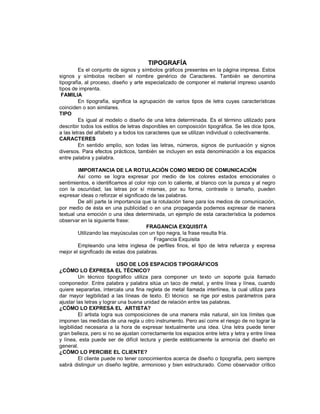
TIPOGRAFÍA
Es el conjunto de signos y símbolos gráficos presentes en la página impresa. Estos
signos y símbolos reciben el nombre genérico de Caracteres. También se denomina
tipografía, al proceso, diseño y arte especializado de componer el material impreso usando
tipos de imprenta.
FAMILIA
En tipografía, significa la agrupación de varios tipos de letra cuyas características
coinciden o son similares.
TIPO
Es igual al modelo o diseño de una letra determinada. Es el término utilizado para
describir todos los estilos de letras disponibles en composición tipográfica. Se les dice tipos,
a las letras del alfabeto y a todos los caracteres que se utilizan individual o colectivamente.
CARACTERES
En sentido amplio, son todas las letras, números, signos de puntuación y signos
diversos. Para efectos prácticos, también se incluyen en esta denominación a los espacios
entre palabra y palabra.
IMPORTANCIA DE LA ROTULACIÓN COMO MEDIO DE COMUNICACIÓN
Así como se logra expresar por medio de los colores estados emocionales o
sentimientos, e identificamos al color rojo con lo caliente, al blanco con la pureza y al negro
con la oscuridad; las letras por sí mismas, por su forma, contraste o tamaño, pueden
expresar ideas o reforzar el significado de las palabras.
De allí parte la importancia que la rotulación tiene para los medios de comunicación,
por medio de ésta en una publicidad o en una propaganda podemos expresar de manera
textual una emoción o una idea determinada, un ejemplo de esta característica la podemos
observar en la siguiente frase:
FRAGANCIA EXQUISITA
Utilizando las mayúsculas con un tipo negra, la frase resulta fría.
Fragancia Exquisita
Empleando una letra inglesa de perfiles finos, el tipo de letra refuerza y expresa
mejor el significado de estas dos palabras.
USO DE LOS ESPACIOS TIPOGRÁFICOS
¿CÓMO LO ÉXPRESA EL TÉCNICO?
Un técnico tipográfico utiliza para componer un texto un soporte guía llamado
componedor. Entre palabra y palabra sitúa un taco de metal, y entre línea y línea, cuando
quiere separarlas, intercala una fina regleta de metal llamada interlínea, la cual utiliza para
dar mayor legibilidad a las líneas de texto. El técnico se rige por estos parámetros para
ajustar las letras y lograr una buena unidad de relación entre las palabras.
¿CÓMO LO EXPRESA EL ARTISTA?
El artista logra sus composiciones de una manera más natural, sin los límites que
imponen las medidas de una regla u otro instrumento. Pero así corre el riesgo de no lograr la
legibilidad necesaria a la hora de expresar textualmente una idea. Una letra puede tener
gran belleza, pero si no se ajustan correctamente los espacios entre letra y entre línea
y línea, esta puede ser de difícil lectura y pierde estéticamente la armonía del diseño en
general.
¿CÓMO LO PERCIBE EL CLIENTE?
El cliente puede no tener conocimientos acerca de diseño o tipografía, pero siempre
sabrá distinguir un diseño legible, armonioso y bien estructurado. Como observador crítico
sabrá cuando los espacios han sido bien utilizados o si en cambio el diseño presenta fallas
en estos aspectos.
FACTORES QUE CONDICIONAN LA LEGIBILIDAD DE UN RÓTULO O TEXTO
DISEÑO DE LA LETRA: existen tipos de letra que facilitan la legibilidad de un texto ya que
sus diseños se ajustan bien a ciertos espaciados. Así, se dice que los tipos de letra latinos y
romanos, cuyo diseño es parecido a los clásicos ofrecen mayor legibilidad.
ESPACIADO ENTRE LETRA Y LETRA: una palabra o frase que tenga las letras poco
espaciadas dificulta la lectura de las mismas y por tanto no ofrecen buena legibilidad.
Igualmente, si éstas están excesivamente espaciadas también resultan difíciles de leer. Así
mismo, un espaciado mínimo e igual entre letra y letra, crea en los rótulos una desagradable
falta de unidad.
Espaciado Normal: TALAVERA
Espaciado Expandido: T A L A V E R A
Espaciado Comprimido: T L V R
AA E A
TAMAÑO DE LA LETRA: las letras grandes son más legibles que las pequeñas. Un tamaño
ideal que favorece la lectura es la letra del cuerpo diez o doce. Las lecturas para niños (libros
de cuentos y de enseñanza primaria) deben componerse en cuerpo doce o catorce.
LONGITUD DE LA LÍNEA: una línea muy larga con letras pequeñas dificulta la lectura, ya
que imprime muchas palabras y hace complejo el pasar de una línea a otra. Lo ideal en un
texto de cuerpo diez o doce, es un mínimo de 40 letras por línea y un máximo de 70, ya que
si sobrepasa este máximo, la lectura del texto puede ser difícil.
ESPACIADO ENTRE LÍNEA Y LÍNEA: mientras más extensa es una línea de texto, y más
pequeño el cuerpo de la letra, más necesario es el espaciado entre línea y línea, llamado en
artes gráficas Interlineado. Entre los más usuales tenemos:
SENCILLO
La tipografía es el conjunto de signos y símbolos gráficos presentes en la página
EL LETRASET: quees un sistema muy difundido, que consiste en componer un rótulo mediante el traslado calcográfico de las letras que lo componen, a partir de una hoja preparada para este tipo de trabajos. LA TIPOGRAFÍA: que es un sistema basado en la fórmula tradicional de componer un rótulo con letra de imprenta, imprimiendo seguidamente una prueba sobre papel. LA ROTULACIÓN FOTOGRÁFICA: en la que se componen los rótulos pegando, una al lado de la otra, letras previamente fotografiadas al tamaño deseado. Es importante destacar que los dos grandes sistemas que permiten obtener pruebas impresas de rótulos o textos, son: la Tipografía, con sus máquinas de Linotipia y Monotipia, y la Fotocomposición, que es un sistema moderno en el cual, los tipos metálicos son sustituidos por impresiones fotográficas sobre clisé o película positiva. PRO Y CONTRAS DE LA APLICABILIDAD DE LA TIPOGRAFÍA EN LOS DISTINTOS ÁMBITOS DEL TRABAJO El uso de las antiguas máquinas tipográficas economiza la impresión, ya que la tinta que utilizan es menos costosa y puede realizar un número mayor de impresiones, además estas máquinas tienen el beneficio de tener hasta 100 años de garantía, como ejemplo, están las máquinas minerva y las rotativas. Uno de los mayores problemas que podrían presentar estas máquinas, es que al dañarse una pieza, ésta es muy difícil de conseguir en el mercado, y entonces se debe mandar a hacer, lo cual sí puede ser costoso. Las técnicas modernas que han sustituido estas máquinas son computarizadas, estas ofrecen el beneficio de diseños de alta calidad de impresión, que pueden ser reproducidos según el tipo de impresora en distintos formatos, pero el problema que estos sistemas presentan es el alto costo de la impresión, debido al uso de cartuchos, láser, etc., y otro problema es que por esa misma razón, el número de impresiones que se puede realizar es mucho menor y las impresoras no son tan duraderas. BIBLIGRAFÍA - Guía Práctica “La Tipografía y la Rotulación”. Venezuela. 1990.